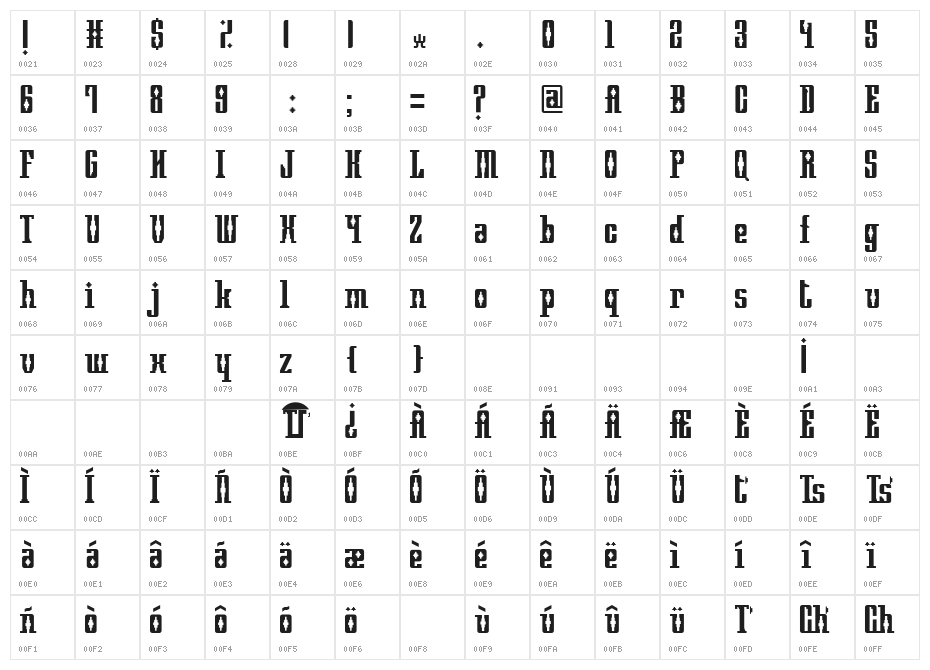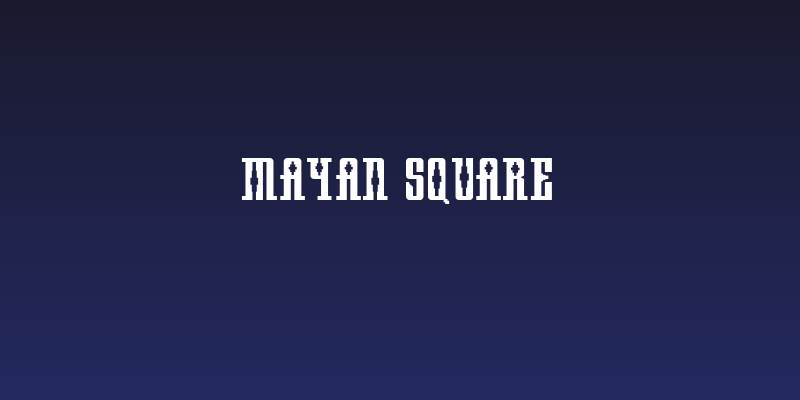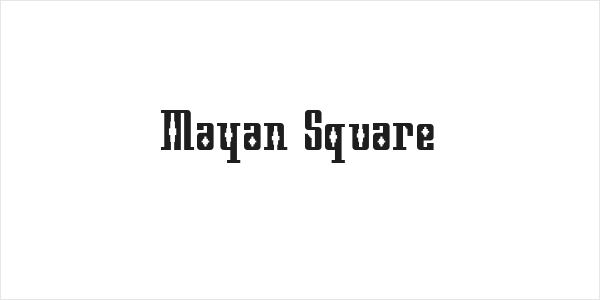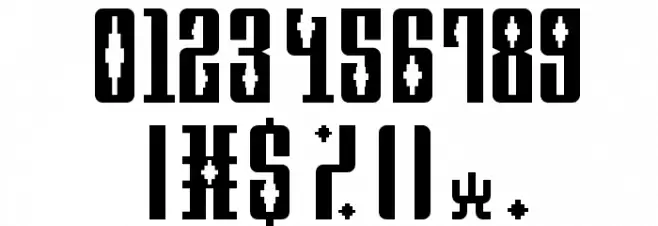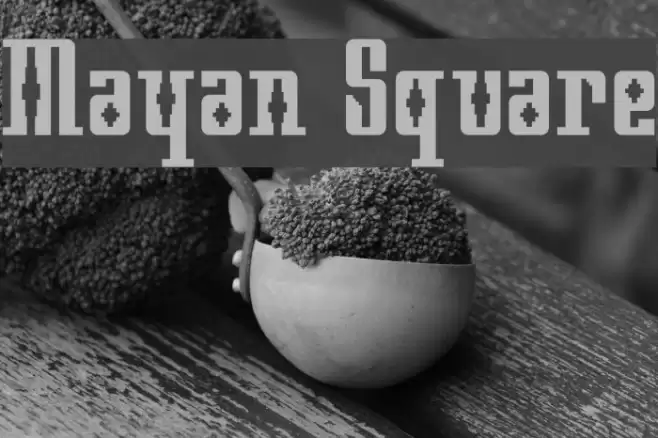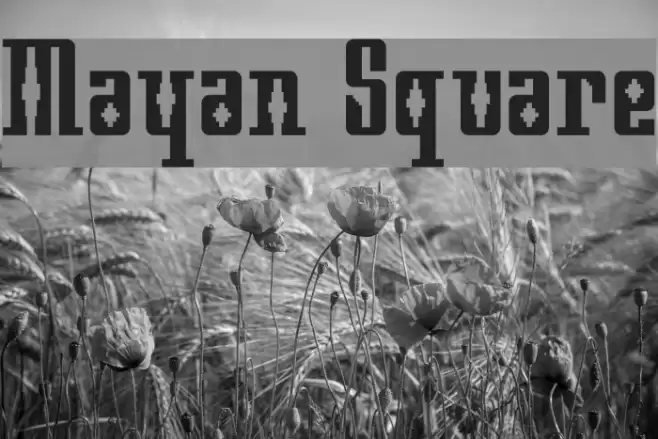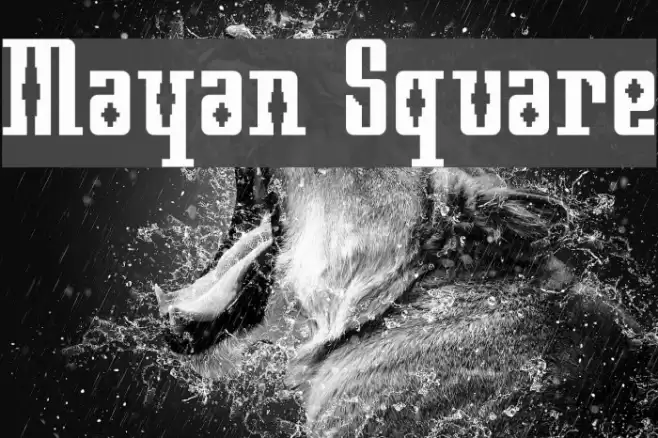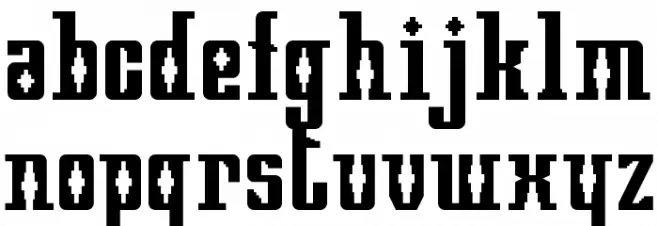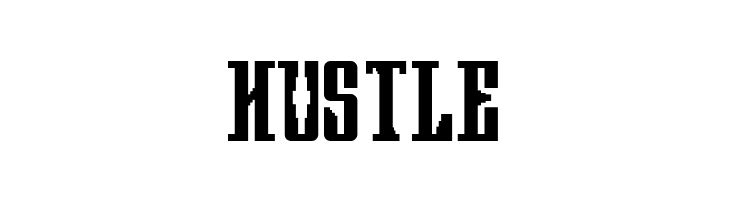
Mayan Square Font
| Projets proposés | Ideal for projects that require a bold, eye-catching typeface such as posters, logos, branding materials, and event invitations. |